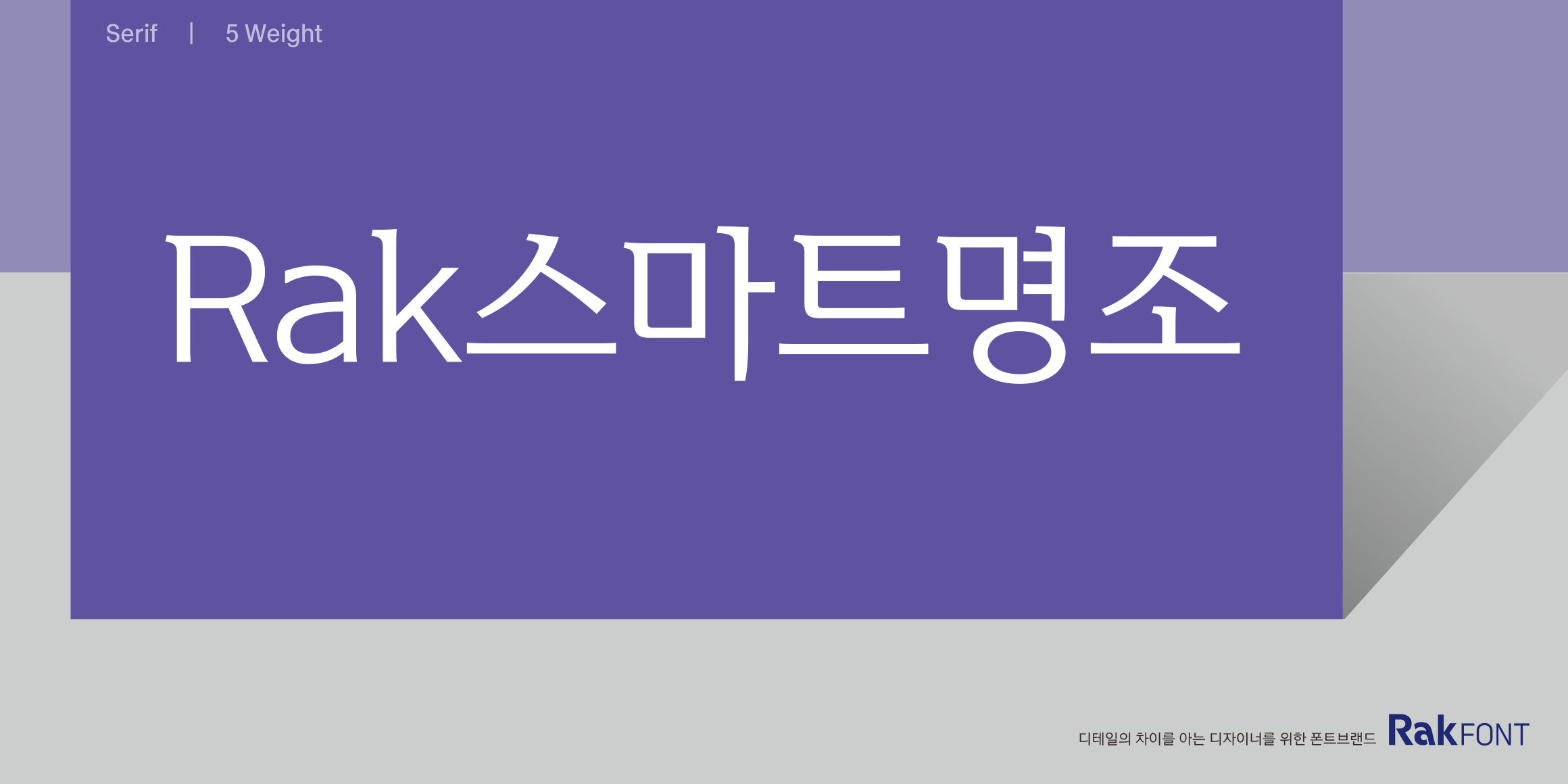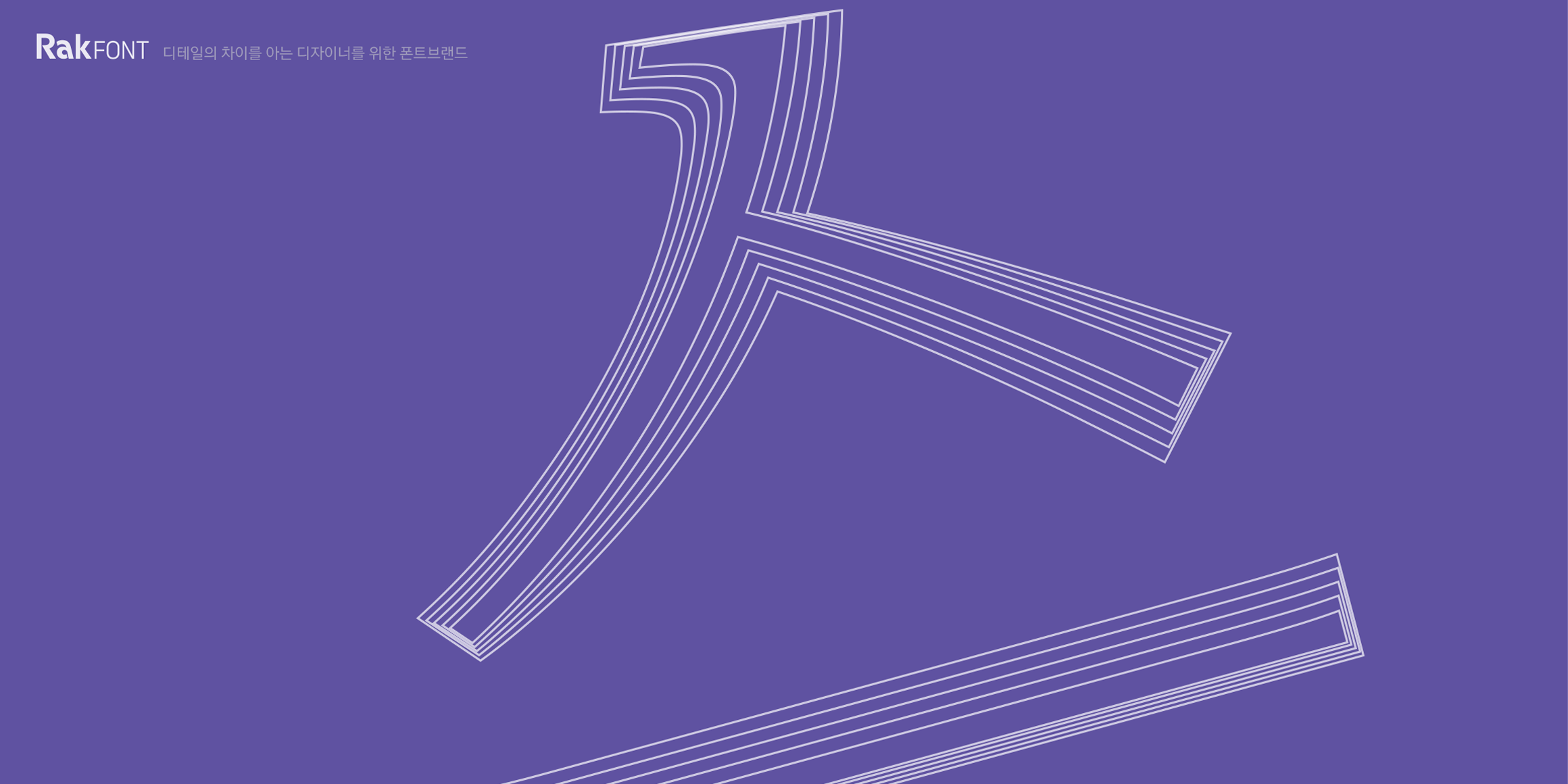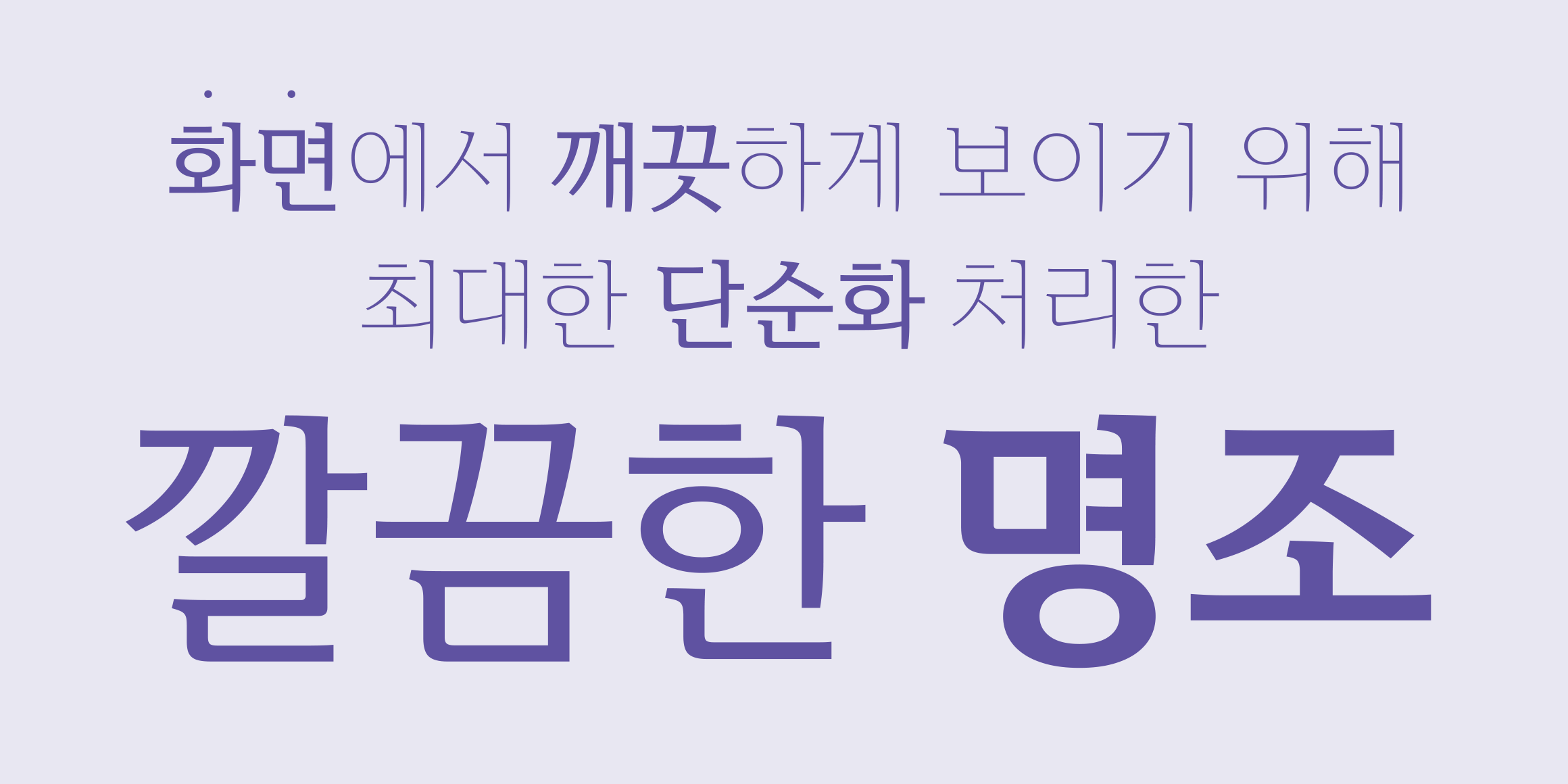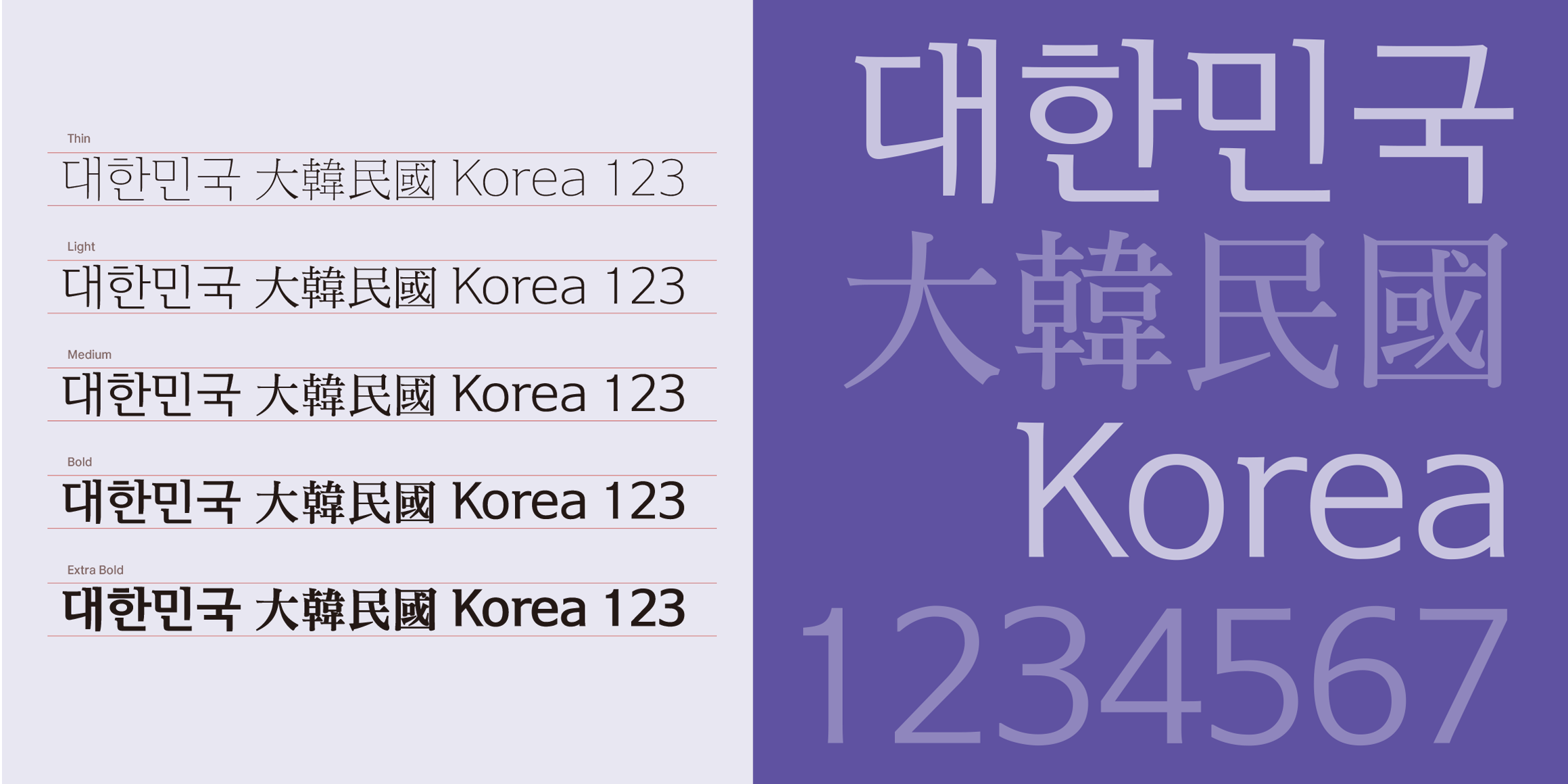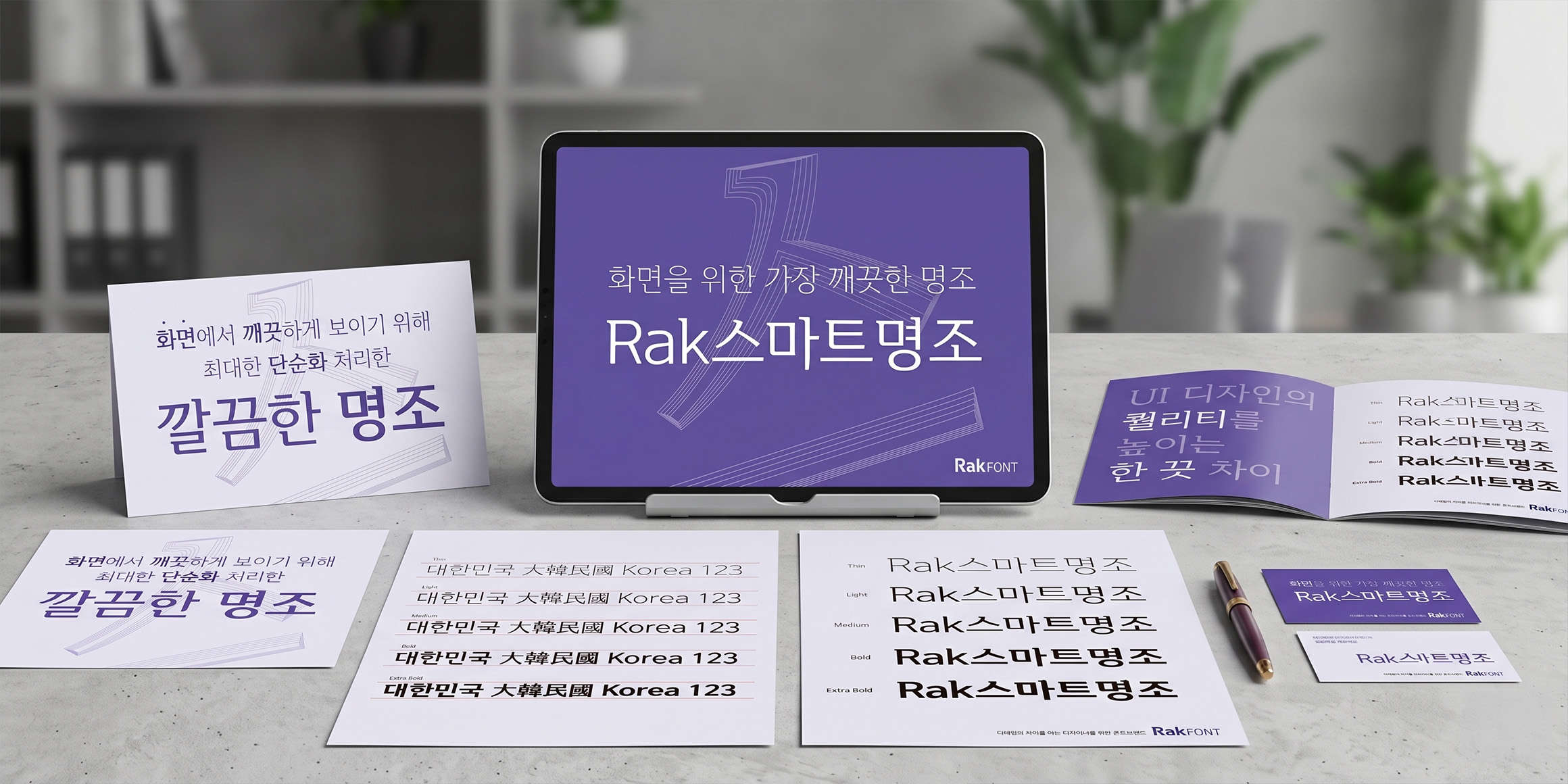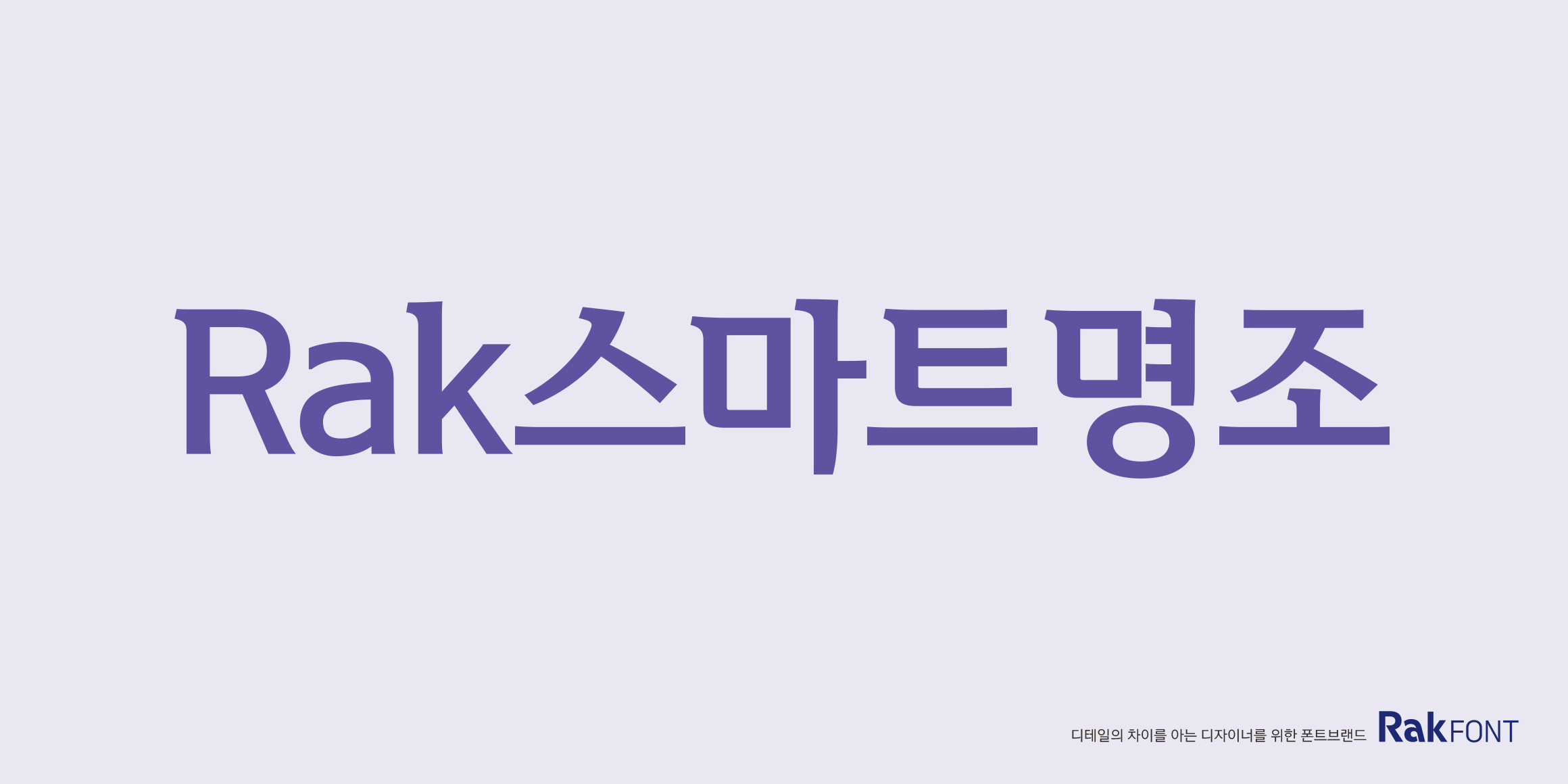
Rak스마트명조
분류 Mincho,Serif,부리
제목용본문용현대적
'Rak스마트명조'는 모바일과 모니터 등 디지털 디스플레이 환경에 최적화된 본문용 세리프 서체입니다. 정체성과 가독성의 균형을 잡는 '락 프로세스'를 바탕으로, 명조체 고유의 우아한 실루엣은 유지하되 화면에서의 렌더링을 저해하는 세리프 요소들은 정교하게 절제했습니다. 웹과 앱 UI 환경에서 픽셀의 뭉개짐 없이 맑고 명료한 텍스트 라인을 구현하며, 디지털 환경에 특화된 스마트한 본문용 명조가 필요한 실무자에게 완벽한 타이포그래피 대안을 제시합니다.
• 박용락
• Mincho,Serif,부리
• 제목용,본문용,현대적,기계적,중립적,모노스페이스